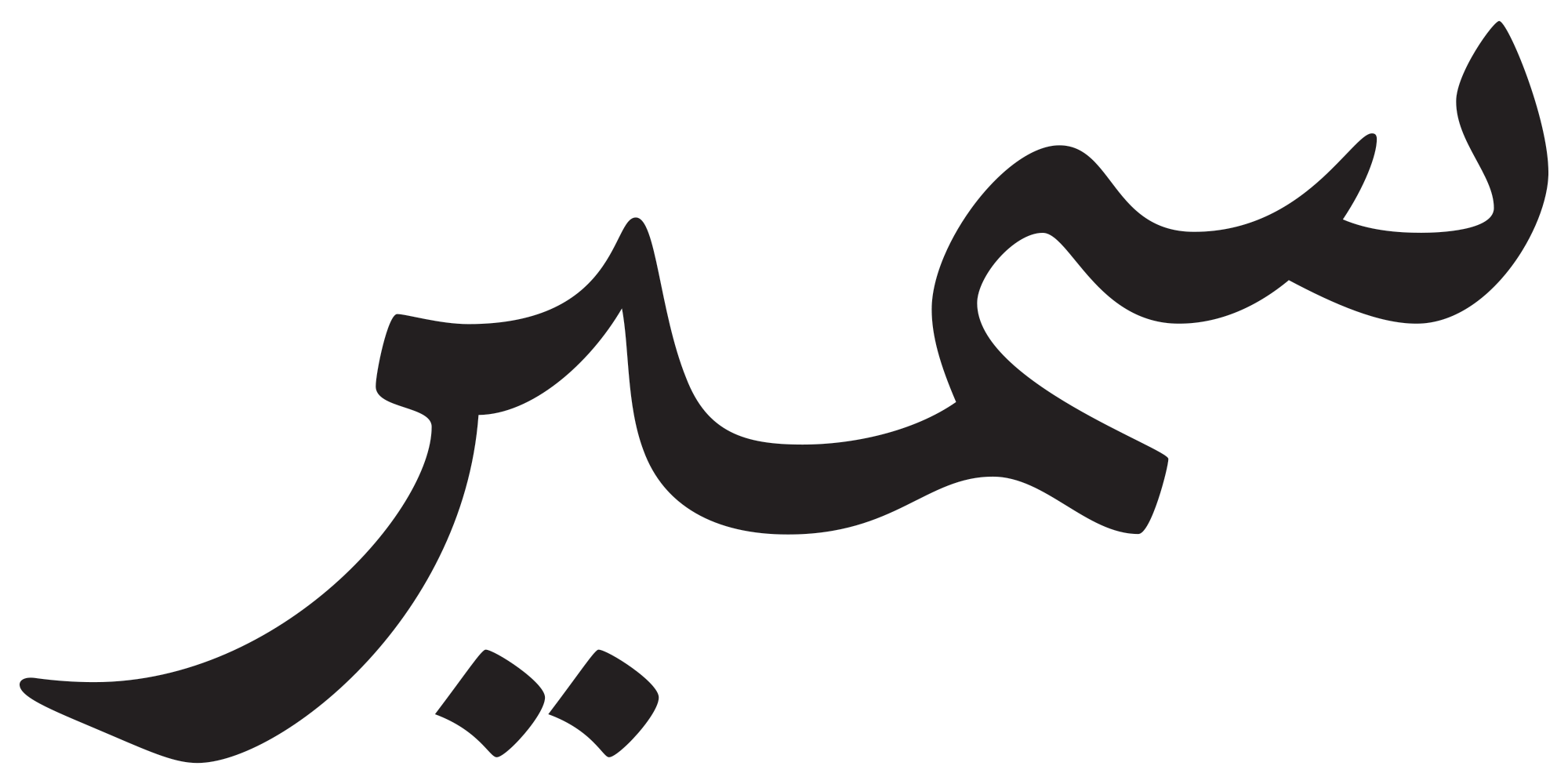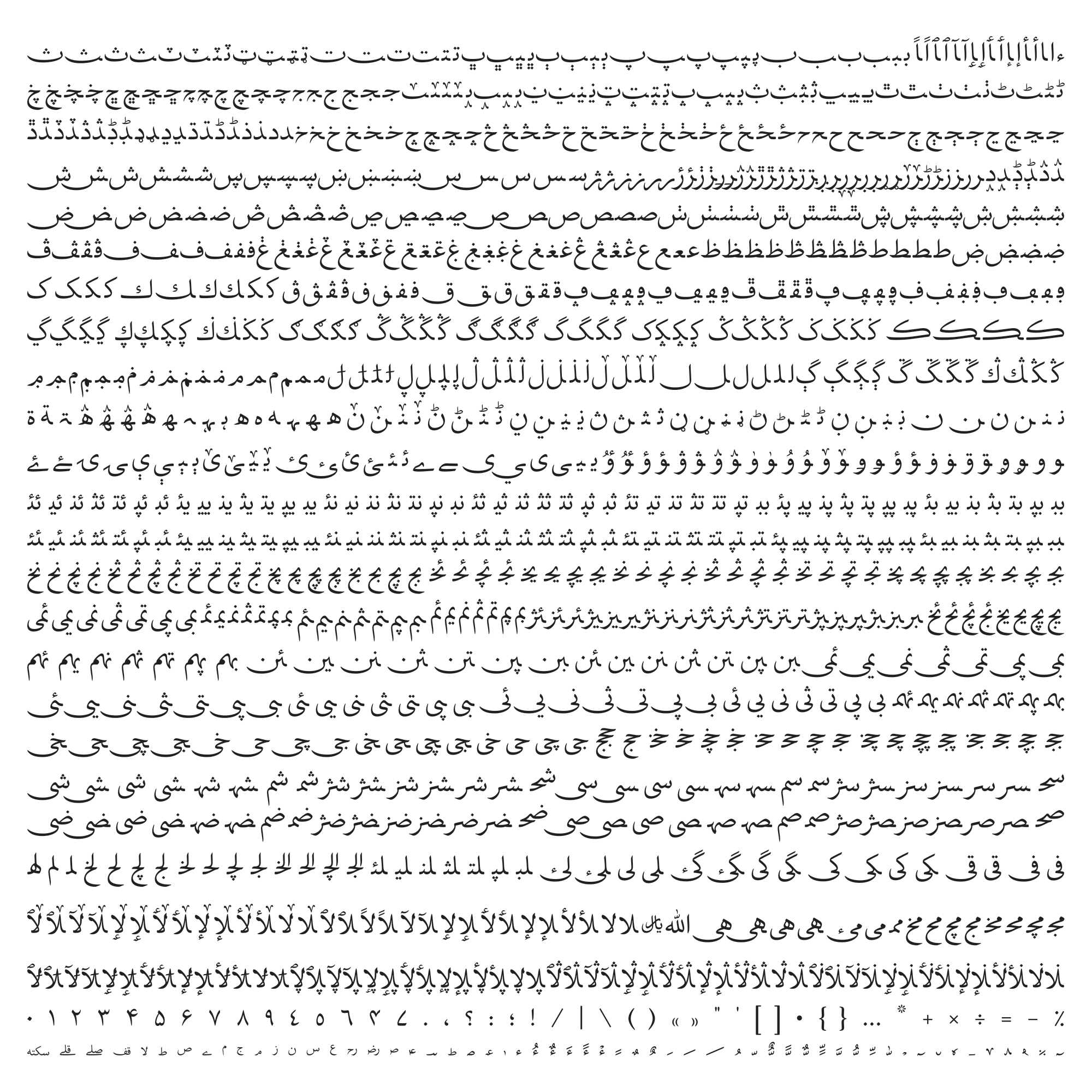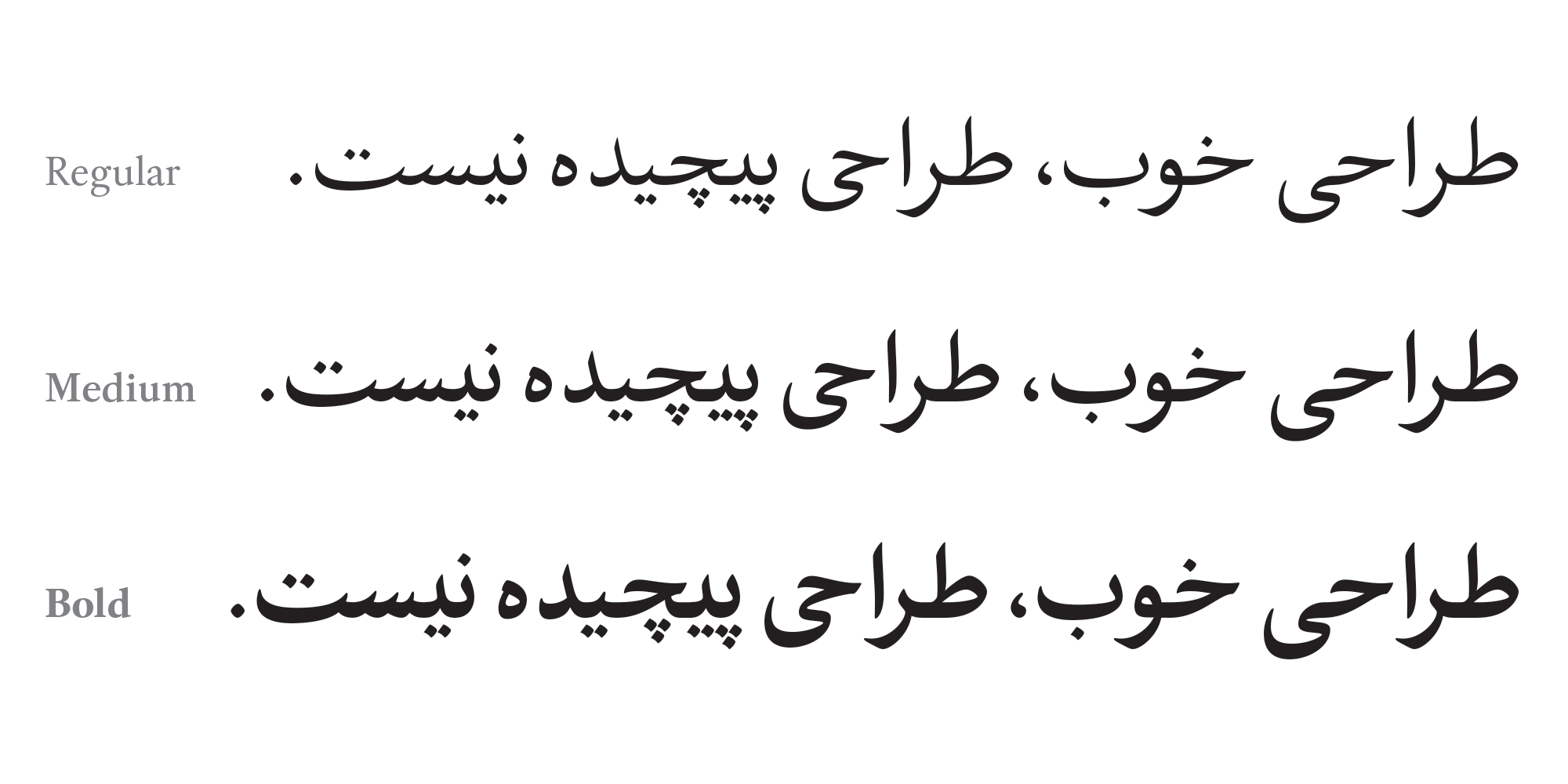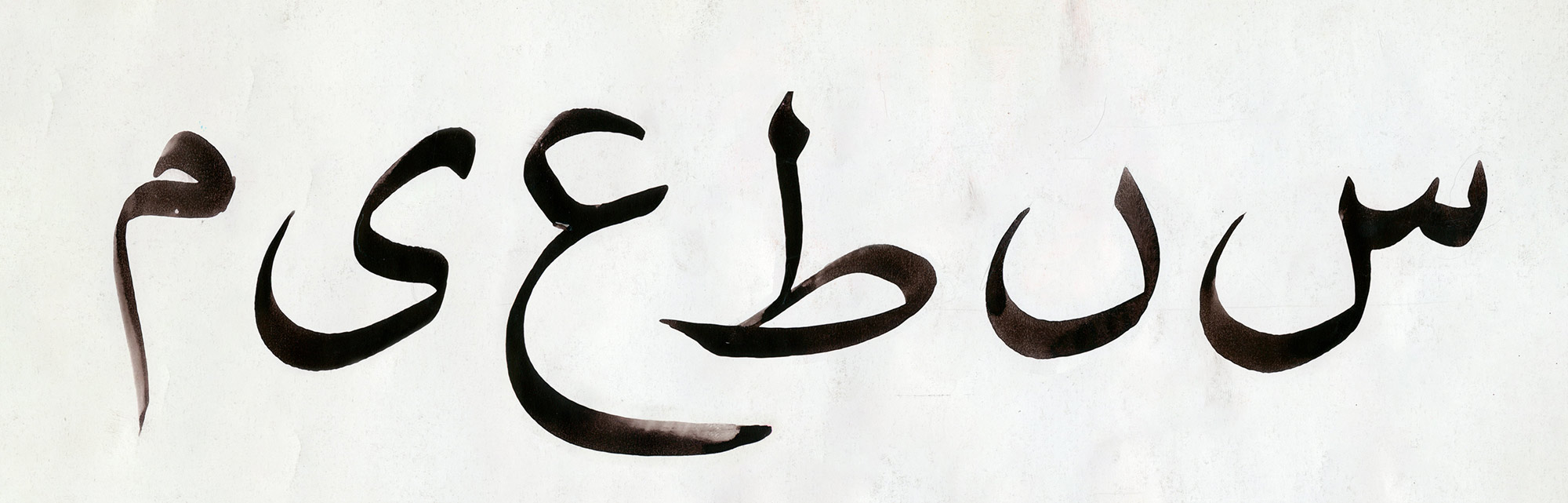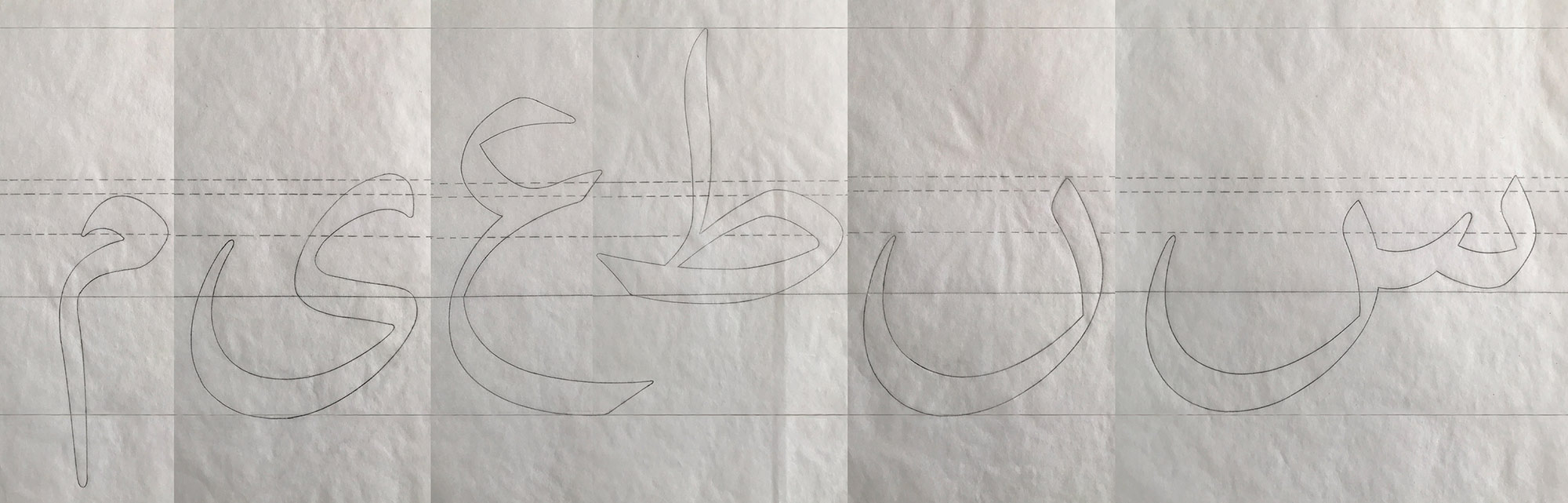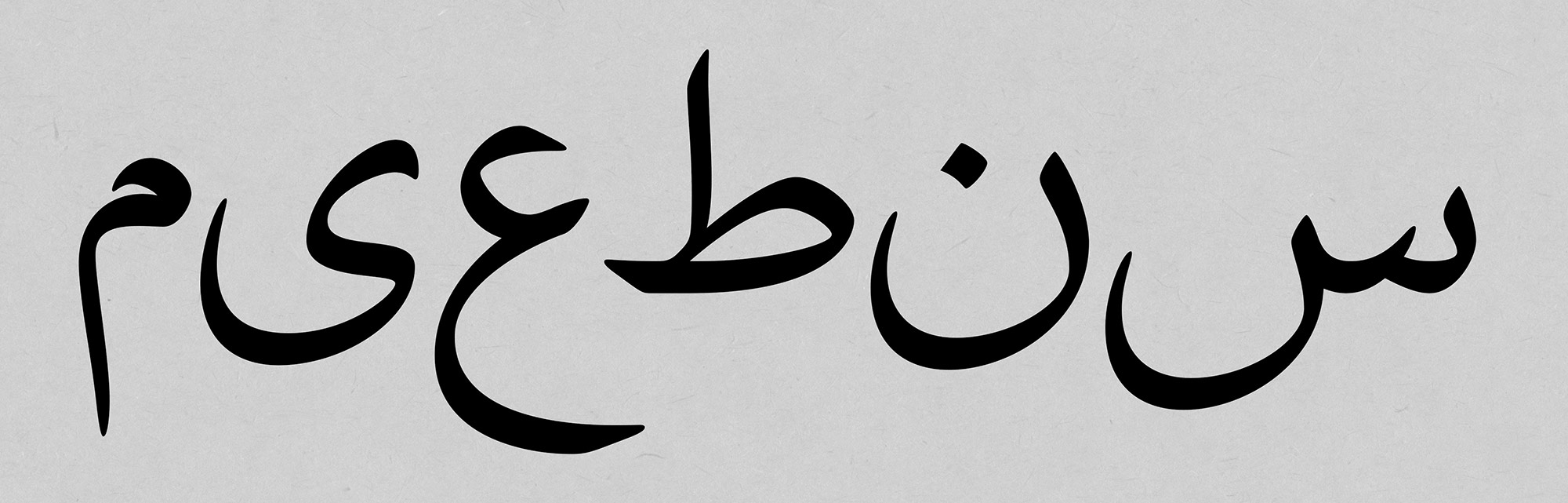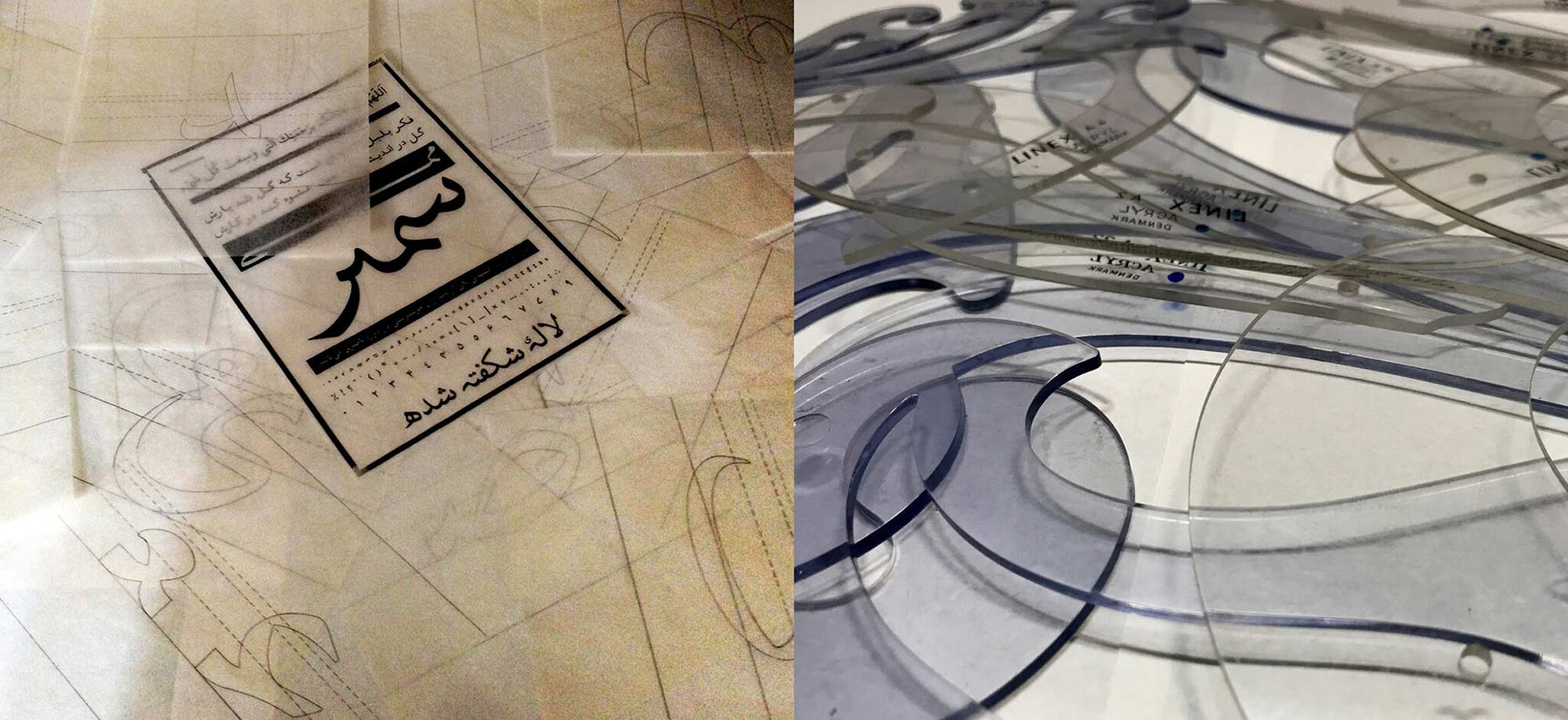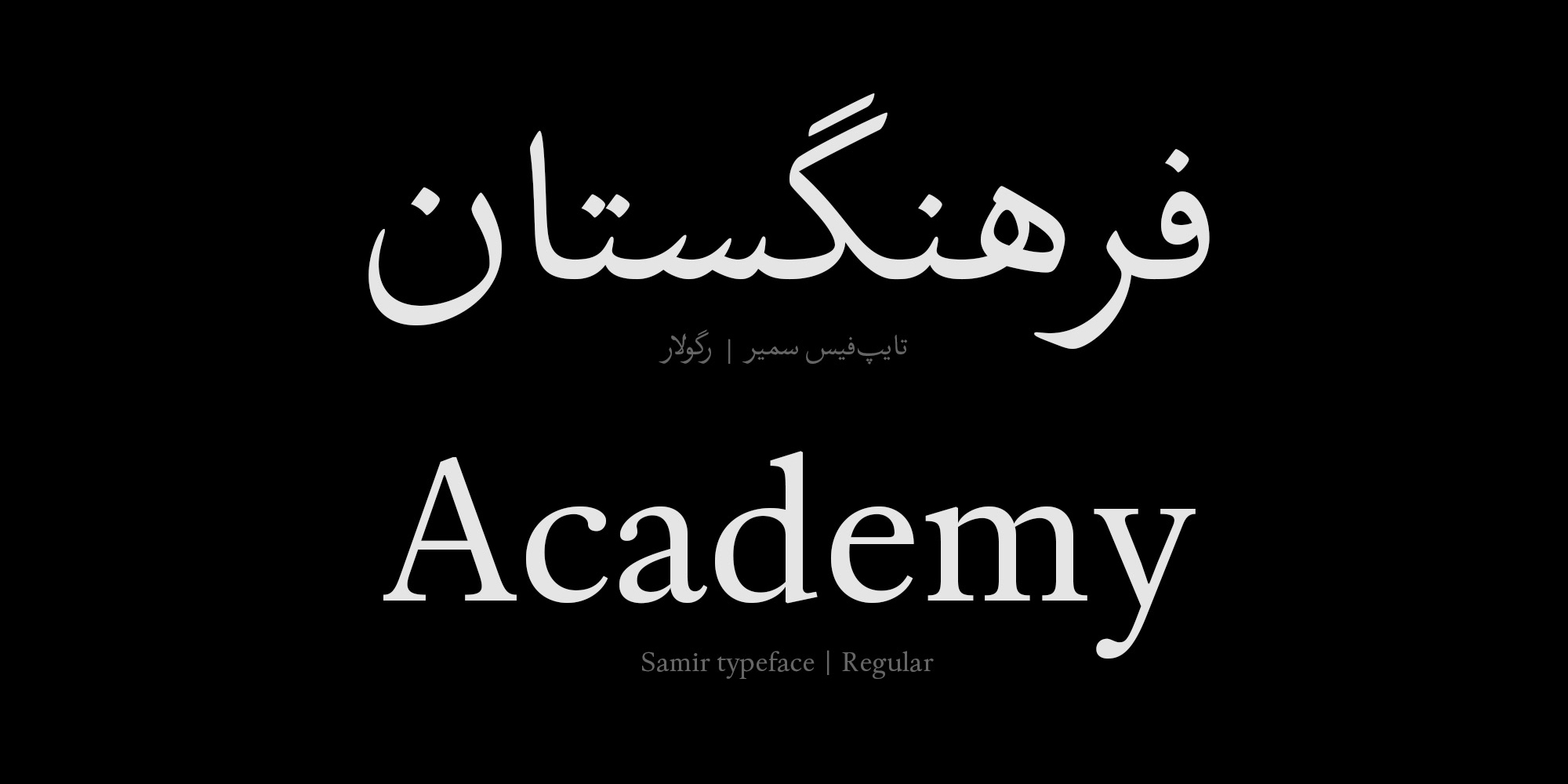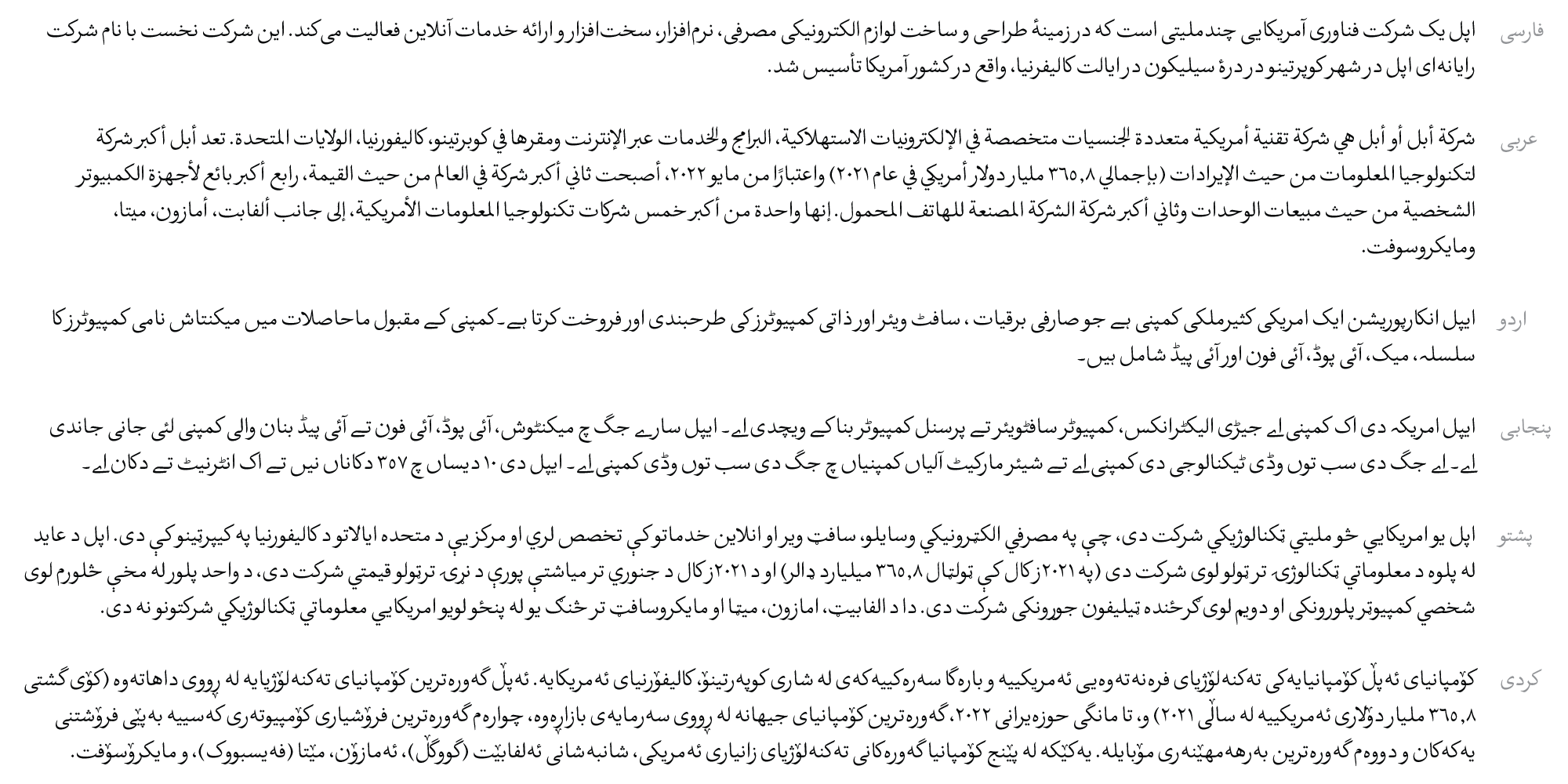
فونت سمیر از زبان فارسی، عربی و انگلیسی پشتیبانی میکند.
فونت سمیر در ۳ وزن معمولی (Regular) میانه (Medium) و تیره (Bold) موجود است. هر ۳ وزن فونت شامل گلیفهای لاتین هستند و در یک قلم منفرد میشود متن را در هر دو زبان لاتین و فارسی تنظیم کرد.
«فونت سمیر» یک تایپفیس با نسبت دور زیاد به سطح است که از خط نسخی که توسط یک خوشنویس به شیوه ایرانی نوشته شده، الهام گرفته شده است. بدین منظور، در ابتدا وحید کرمی که خوشنویسی توانا است منابع اولیه این تایپفیس را کتابت کرد و ترکیبها و مفردات را به سبک خاص خود نوشت. رضا غفاری بر اساس این خطوط، حروف را طی چندین مرحله تغییر داد و با درست کردن متون مختلف اقدام به اصلاح نتیجهی نهایی کرد تا حروف را به سبکی که اکنون در «فونت سمیر» میبینید، تبدیل کند.
این مراحل شامل یک فرآیندی چند ساله است که ابتدا حروف با دست و با استفاده از تعداد زیادی پیستولهی طراحی به شکلی کاملا تمیز و مرتب و با حساسیت بسیار بالا بر روی کاغذ پوستی طراحی شد. تا آنجایی که امکانش وجود داشت سعی شده طراحیهایی که بر روی کاغذ پوستی انجام میشد به طراحی نهایی در نرمافزار نزدیک باشند. به گونهای که حتی یکی از دانشجویان در کلاس تصور میکرد طراحیهای روی کاغذ پوستی توسط پرینتر چاپ شدهاند نه از طریق دستان رضا. نتیجه، مجموعهای از حروف است که زیبایی، وضوح و کیفیت را به نمایش میگذارد و آن را به گزینهای عالی برای کاربردهای مختلف از جمله کتاب، مجله، پوستر و حتی تبلیغات محیطی تبدیل میکند.
برای طراحی حروف لاتینِ این تایپفیس، رضا غفاری و بهمن اسلامی با استفاده از اسپسیمنهای حروف Caslon سبک قدیمی سعی کردهاند با احیا و نزدیک کردن حس و حالِ این حروف به تایپفیس «سمیر»، حروف لاتینِ مناسبی برای این تایپفیس طراحی کنند تا در زمان استفاده از حروف فارسی و لاتین فونت سمیر شاهد سبکی یکسان و خاکستری یکدست باشید. پس تمامی حروف داخل این تایپفیس به شکلی دقیق برای شما طراحی شدهاند تا هماهنگی خارقالعاده را با هم به نمایش بگذارند.
از دیگر ویژگیهای قابل توجه «فونت سمیر» پشتیبانی گسترده آن از خطوط برگرفته از خط عربی است که این تایپفیس را به گزینهی مناسبی برای چاپ یا نمایش زبانهای مختلف زیر شاخهی این خط تبدیل میکند.
در «فونت سمیر»، ویژگیهای منحصر به فردی مانند حروف جایگزین برای حروفی مانند «ر» ، «ح» ، «ک» ، «م» ، «ه» ، «ی» و لیگیچرهای بسیار زیاد را مشاهده میکنید که به شما انتخاب بیشتری را برای خلاقیت در تایپوگرافی فراهم میکند. علاوه بر این، وجود حروف کشیده مانند «ب» ، «ن» ، «ی» و غیره به ترکیببندیهای شما حسی میبخشند که در نمونههای مشابه اگر نایاب نباشد؛ به سختی دستیافتنی است.
«تایپفیس سمیر» در اولين دوره سرو نقرهای انجمن صنفی طراحان گرافیک ایران در سال ۱۳۸۹، موفق به دریافت دیپلم افتخار گردید.